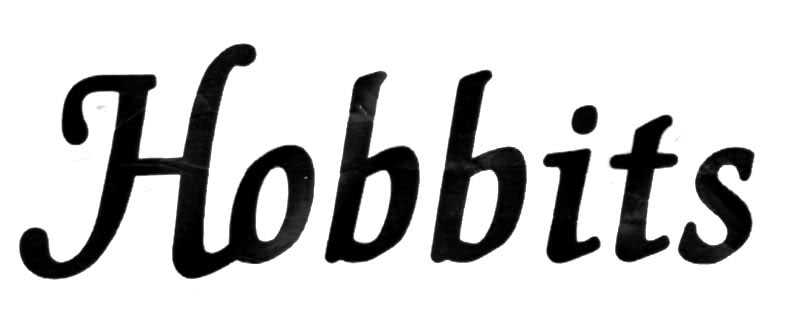
Schrift Brand Hobbits
habe mich jetzt dusselig gesucht und What the font konnte mir auch nicht weiter helfen.
Hat jemand eine Ahnung, welche Schrift das ist?
zumindest in die nähe kommt die hier:
Ich komm viel näher! :cheer: Man nehme das Medici Script:
Und verfette es total, vergrößere das H ... Aber so richtig passen tut das auch nicht ... Vielleicht steckt da viel Mauswerk dahinter?